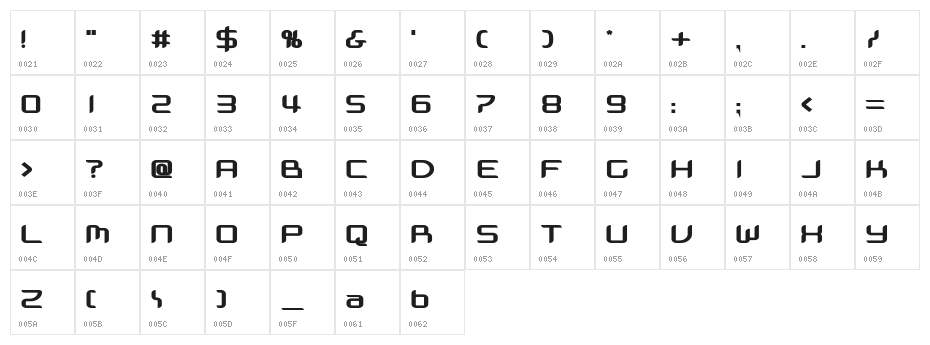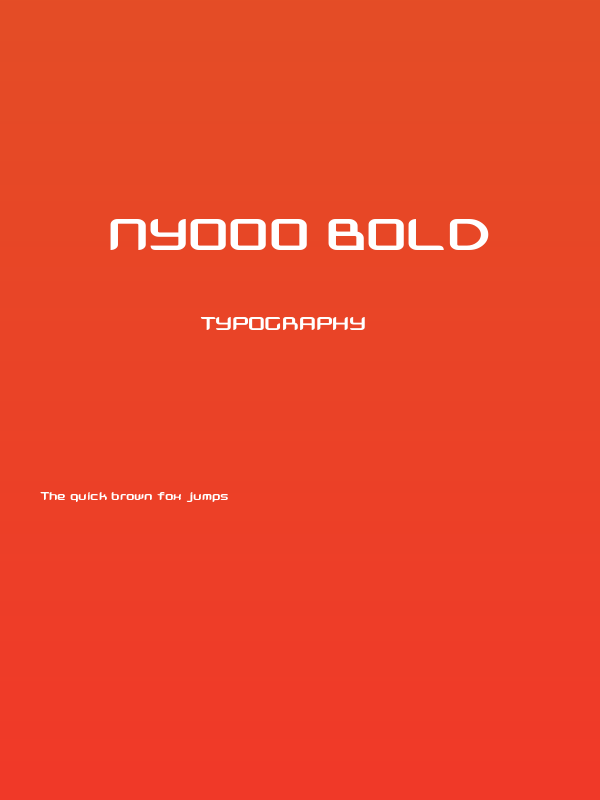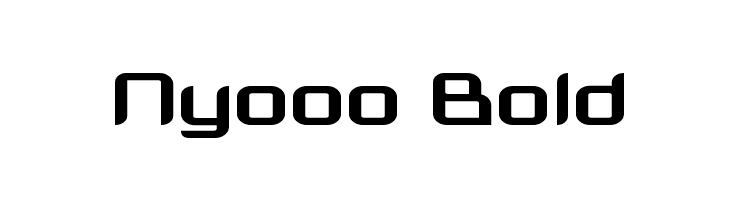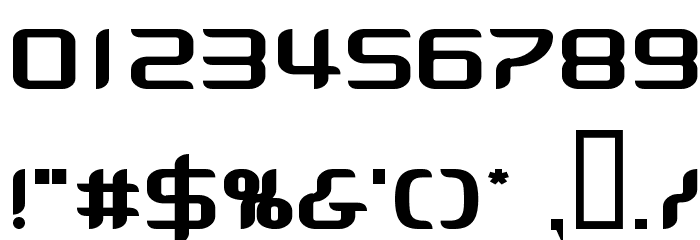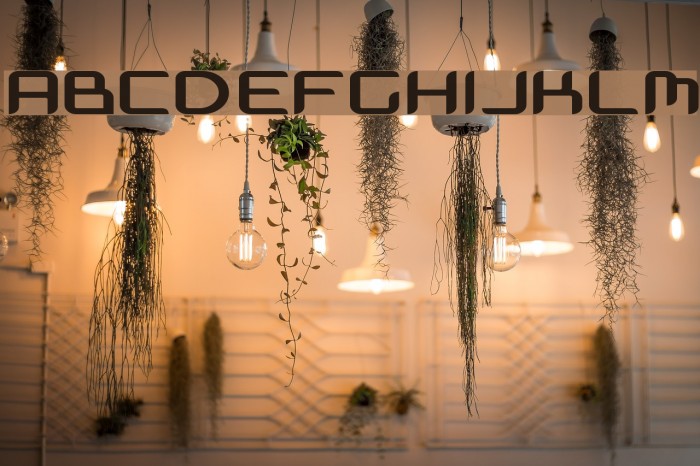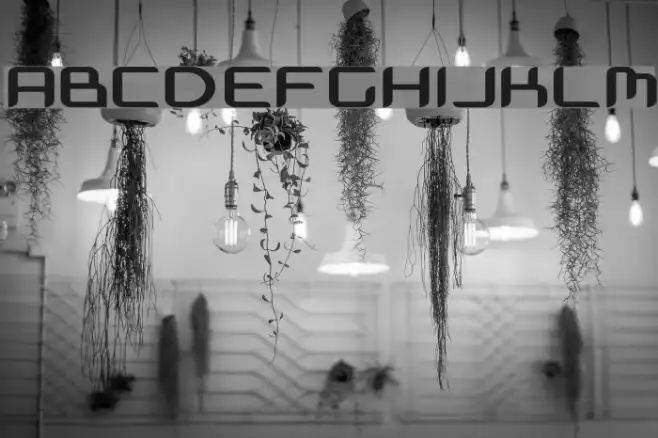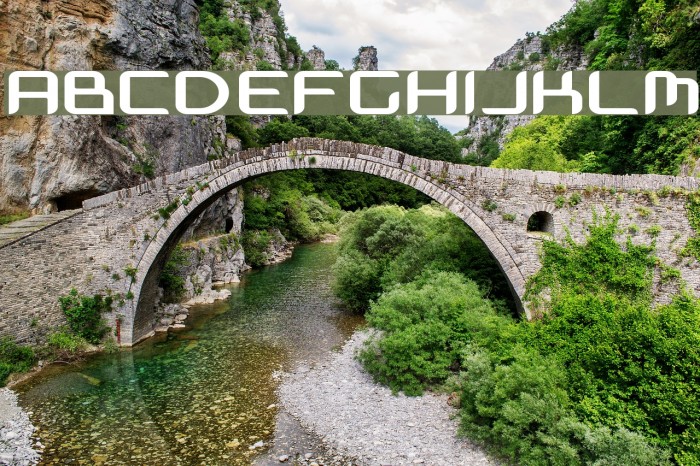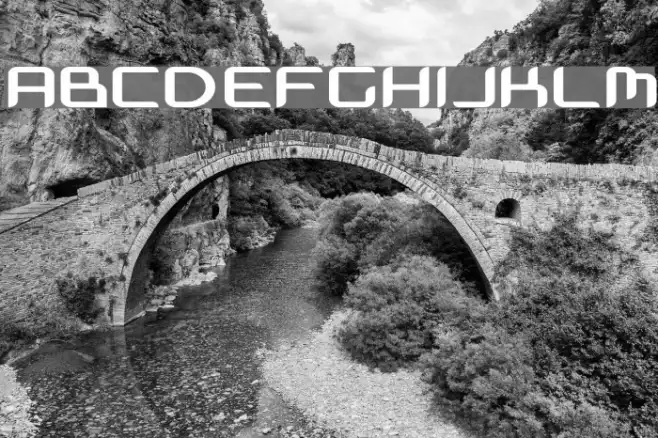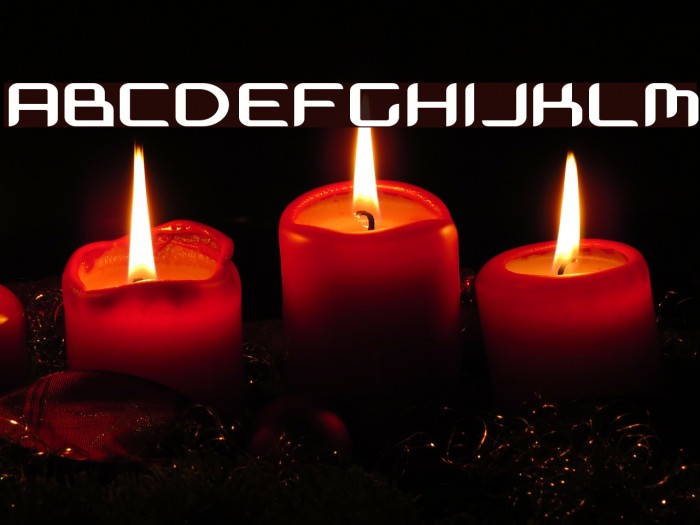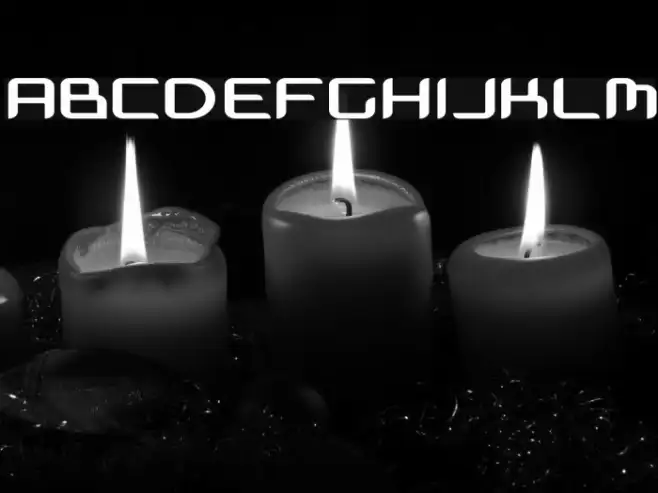
Nyooo Bold Font
| Caso d'uso | Headlines, Logos, Digital Interfaces |
| Progetti proposti | Ideal for technology branding, modern advertising, digital interfaces, and futuristic designs. |
Nyooo Bold